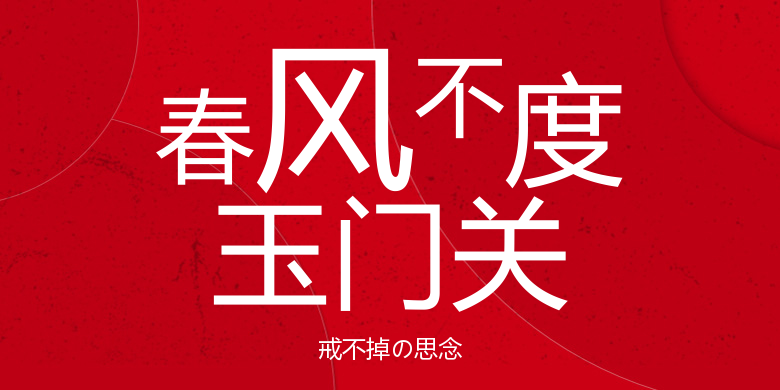
戒不掉の思念
戒不掉の思念,这款字体结构工整、笔画清晰,兼顾美观与易读性,适用于标题、正文、海报、包装、LOGO 等多种场景。字形优雅稳定,风格百搭耐看,适配日常排版与创意设计,让文字呈现更舒适、更具质感。戒不掉の思念一笔一画,皆是细节,以均衡的比例、流畅的线条打造舒适视觉体验,字形端正大气,风格简约现代。无论是商业设计、品牌宣传还是日常排版,都能轻松驾驭,让文字更有格调与力量。戒不掉の思念字体下载。